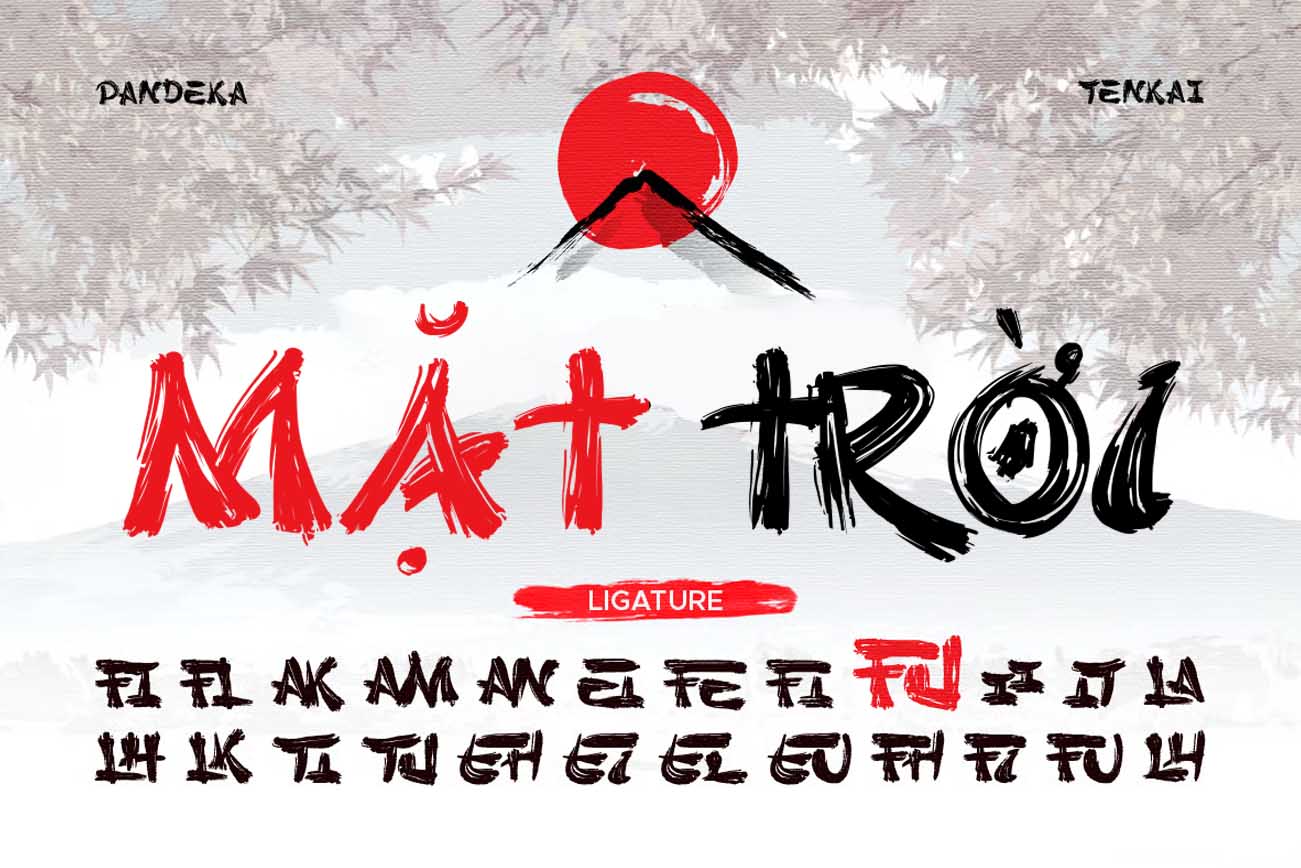
TH Tenkai – Font Chữ Nhật Bản & Brush Nét Cọ Xưa
Nếu bạn đang tìm kiếm một "linh hồn" thực sự cho các thiết kế mang đậm màu sắc văn hóa Á Đông, TH Tenkai chính là mảnh ghép còn thiếu. Đây là dòng font chữ Nhật Bản (Japanese Style) được mô phỏng từ những nét cọ mực (Brush) đầy ngẫu hứng và mạnh mẽ của các võ sĩ Samurai xưa. Không gò bó trong các quy tắc typography chuẩn mực, TH Tenkai toát lên vẻ đẹp của sự bất toàn (Wabi-sabi), nơi những vết xước của cọ khô và độ đậm nhạt bất quy tắc tạo nên một thị giác vô cùng ấn tượng và chân thực.
Sức mạnh của TH Tenkai nằm ở khả năng truyền tải năng lượng ("khí"). Với các nét phẩy sắc lẹm và dứt khoát, bộ font này cực kỳ phù hợp để làm font thư pháp hiện đại cho các poster võ thuật, tựa game kiếm hiệp, hoặc các ấn phẩm truyền thông cho nhà hàng Nhật Bản (Sushi, Ramen). Sự phóng khoáng trong từng ký tự giúp tiêu đề của bạn nổi bật ngay lập tức, phá vỡ sự đơn điệu của các font chữ sans-serif thông thường, đồng thời gợi lên cảm giác thủ công, nghệ thuật và đầy tính chiến đấu.
Về nguồn gốc, bộ font này là sản phẩm sáng tạo của Dharmas Studio (hoặc Pandeka Studio tùy phiên bản phát hành), nổi tiếng với các thiết kế mang đậm bản sắc văn hóa phương Đông. Hiểu được nhu cầu sử dụng font phong cách Nhật tại Việt Nam rất lớn nhưng thường gặp lỗi dấu, Team TH đã tiến hành Việt hóa trọn bộ TH Tenkai. Các dấu câu tiếng Việt được đội ngũ Team TH vẽ lại tỉ mỉ theo đúng nét cọ gốc, đảm bảo khi gõ tiếng Việt, dòng chữ vẫn giữ được sự liền mạch và thần thái dũng mãnh vốn có.